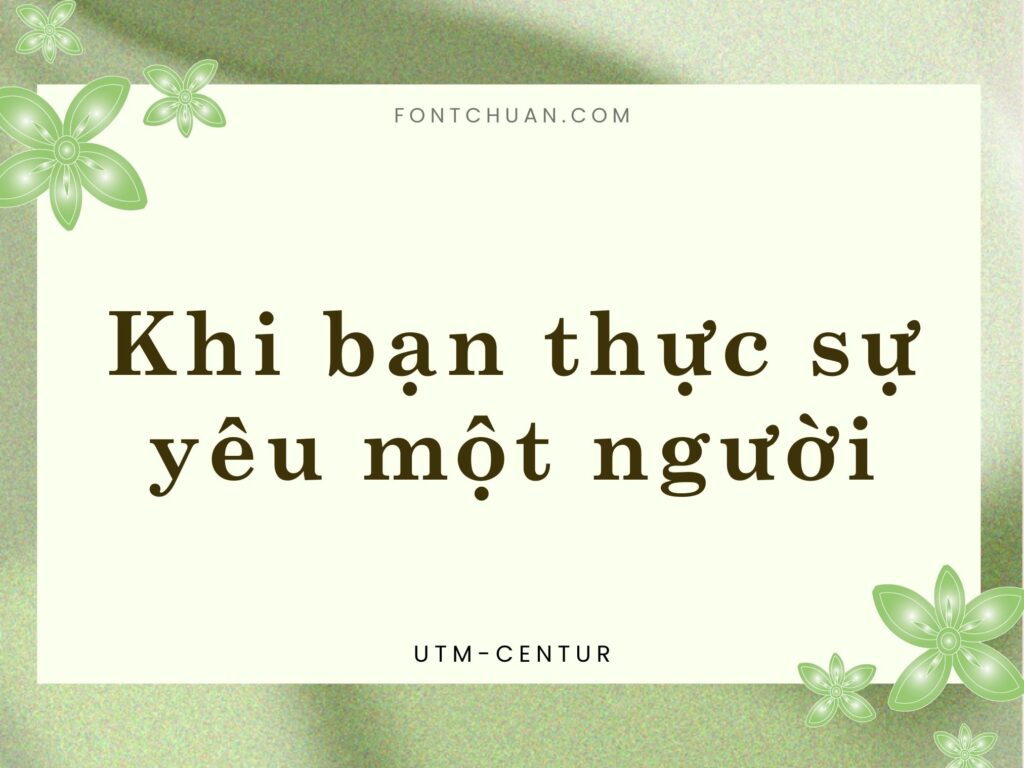
Font UTM Centur Trọn Bộ Việt Hóa
UTM Centur là phiên bản Việt hóa của font chữ Centur, một kiểu chữ serif cổ điển với thiết kế thanh lịch và dễ đọc. Font này nổi bật với các ký tự có chân rõ ràng, đường nét cân đối, tạo cảm giác chuyên nghiệp và trang nhã. Phiên bản Việt hóa đã được thực hiện bởi Công ty TNHH Vitoen, hỗ trợ đầy đủ tiếng Việt cùng hơn 100 ngôn ngữ khác. Đây là một trong những font được thành viên Font Chuẩn sưu tầm và chọn lọc nhằm phục vụ nhu cầu thiết kế chuyên nghiệp và hiện đại.
UTM Centur có cấu trúc chữ với độ tương phản nhẹ giữa các nét thanh đậm, chân chữ sắc nét và tỷ lệ ký tự cân đối, tạo nên khả năng đọc tốt cả trên bản in và kỹ thuật số. Font này rất phù hợp với thiết kế sách, tiêu đề, tài liệu học thuật, hồ sơ thương hiệu hoặc các ấn phẩm đòi hỏi sự trang trọng và rõ ràng. Những ngành nghề như quảng cáo, giáo dục, công nghệ và bất động sản có thể tận dụng UTM Centur để thể hiện sự chuyên nghiệp và uy tín trong thiết kế.